Seguimos con esta particular selección de tipografías de Adobe Fonts. En la primera entrega, que puedes encontrar aquí, hablamos de serif, sans grotescas, sans geométricas y sans humanistas.
Esta segunda entrega vamos a dedicarla exclusivamente a las tipografías display, quizá la categoría tipográfica más amplia que podemos encontrar. Destinadas principalmente para el gran formato (cartelería, titulares…) las display o tipografías de visualización son formalmente muy variadas, y oscilan entre lo más convencional y lo más radicalmente experimental, pero todas ellas con el denominador común de la búsqueda de la expresividad, término con el que también se empiezan a conocer: tipografías expresivas.
Una vez situados, hablemos ahora de algunas de las display que podemos encontrar en Adobe Fonts.
Obviously y Swear Display, de OHNO TYPE
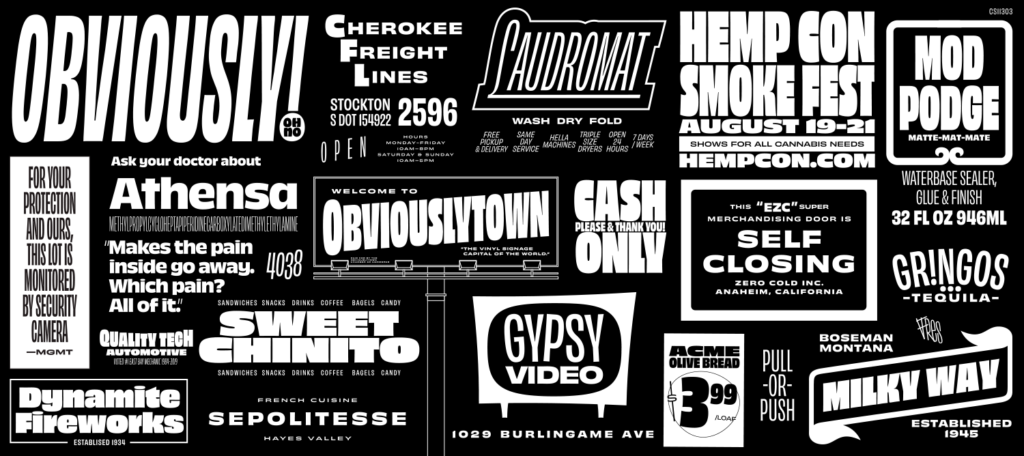
La tecnología variable se lleva de maravilla con las display y Obviously es buena muestra de ello. Una superfamilia compuesta por nada menos que 96 estilos —seis anchos, ocho pesos, tanto en redonda como en itálica—, con todo el sabor de la gran tradición de los rotulistas estadounidenses. «La sutileza es para los pájaros», dice el singular James Edmondson en la descripción, pero la expresividad de Obviously está llena de sutilezas —como todos sus excelentes trabajos— que aumentan exponencialmente gracias al movimiento.
Seguimos con Edmondson, quien en alguna ocasión ha confesado que comienza diseñando en tamaños de visualización y que de ahí pueden surgir tamaños más pequeños, adecuados para texto. Esto explica que Swear sea como una exploración de las posibilidades expresivas y estilísticas del estilo romano
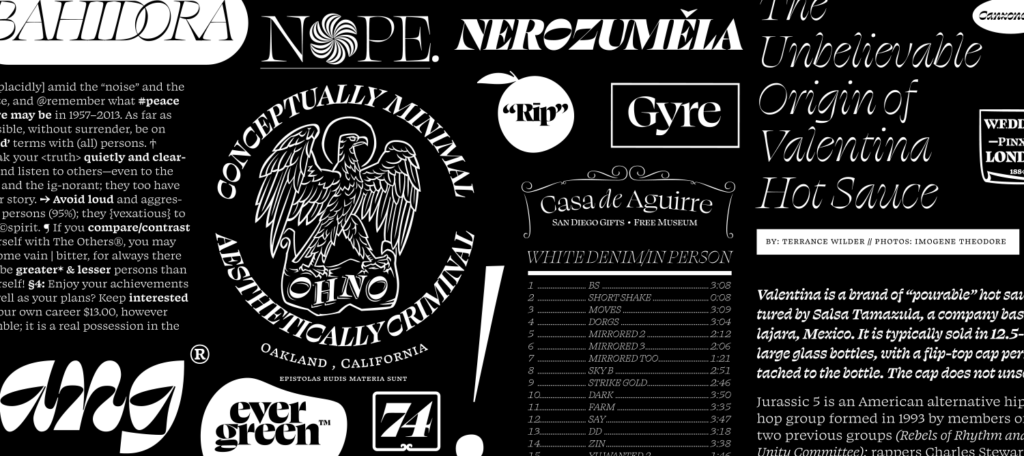
A lo largo de sus tres estilos — text, banner y display— juega con los contrastes, los remates, las curvas e incluso con ligaduras dentro de un mismo carácter, como en el caso de la W. No hay duda de que Edmondson se ha divertido diseñándola, algo que queda patente en la frescura y brillantez de Swear Display.
Termina, de Fort Foundry
Con sede en la ciudad estadounidense de Athens, en el estado de Georgia, localidad natal de los gloriosos R.E.M., Fort Foundry se describen a sí mismos como una fundición que se divierte diseñando tipografías funcionales. Y de manera más pronunciada que sus compatriotas de OHNO TYPE, su catálogo rezuma rotulismo americano.
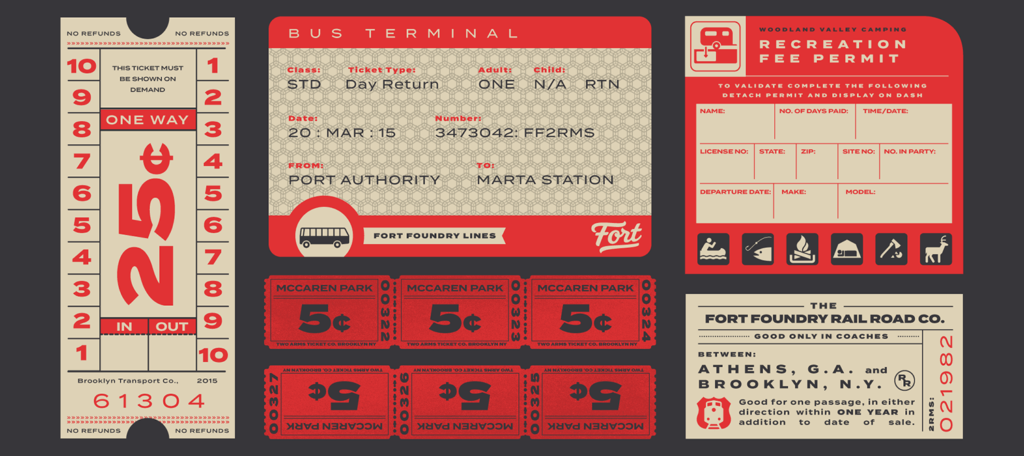
Un buen ejemplo de ello es Termina, que juega con el espíritu de las geométricas y la generosidad de las proporciones de las display. Una considerable altura de x y una majestuosa anchura le confieren nitidez y legibilidad y por tanto la convierten en una tipografía polivalente, con excelentes resultados, por supuesto, en tamaños grandes, pero también en textos de una cierta extensión.
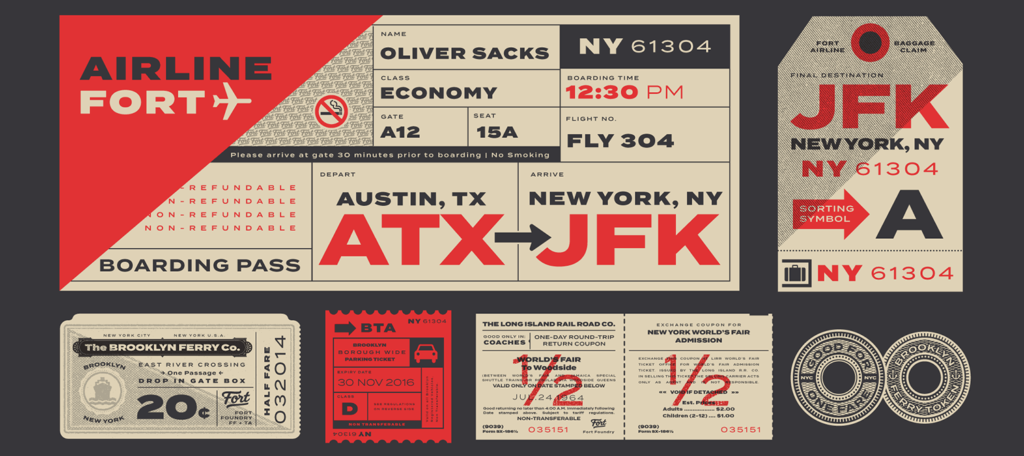
Ella y Sisters de Laura Meseguer
Ella es muchas cosas. Según la propia Meseguer, se trata de una síntesis entre el estilo stencil y la caligrafía. Pero Ella presenta cuatro estilos bien diferenciados, aunque todos ellos bajo esta misma premisa. Romano, uncial, rústico —unas evoluciones de la escritura romana que convivieron durante la misma época—, además de un cuarto llamado brutalista, conviven armoniosamente en este brillante artefacto tipográfico.
Ella es ganadora del TDC 2023 y obtuvo un Certificado de Excelencia Tipográfica
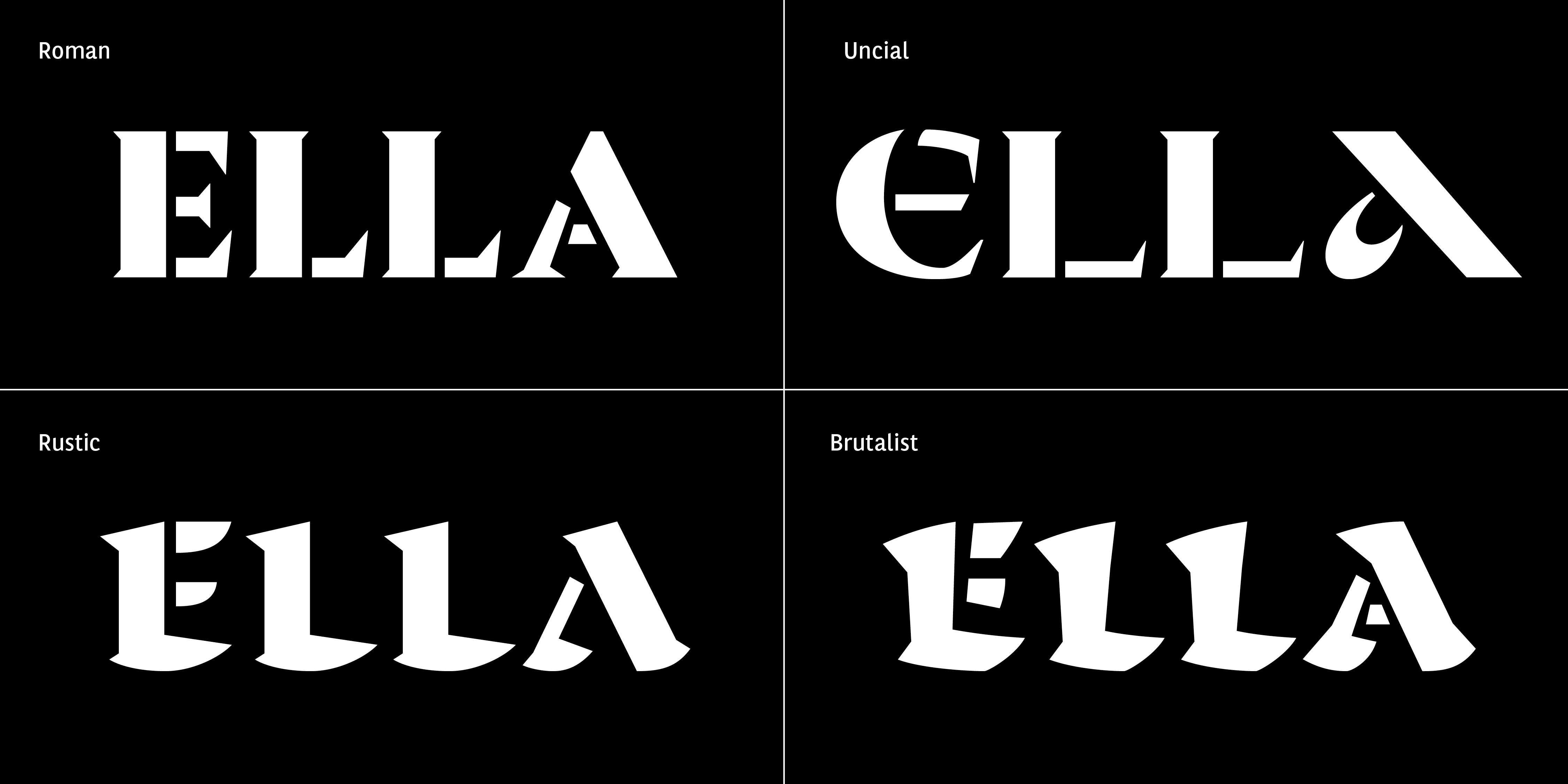
De nuevo Meseguer indaga en las posibilidades del estilo stencil. Caracteres deconstruidos, cuyas partes se hermanan —de ahí el nombre— y se complementan entre sí, «celebrando sus diferencias». Las modulaciones de contraste y demás características formales dan lugar a cuatro estilos, distintos pero hermanados. Sisters se presenta sólo en mayúsculas, lo que reafirma su carácter puramente display.
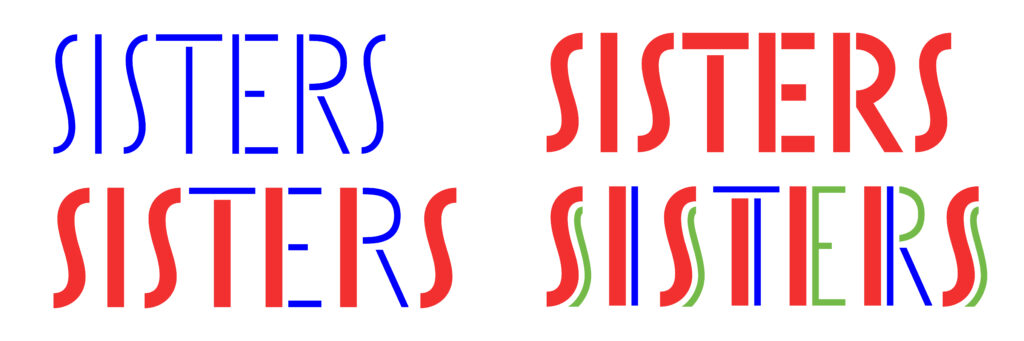
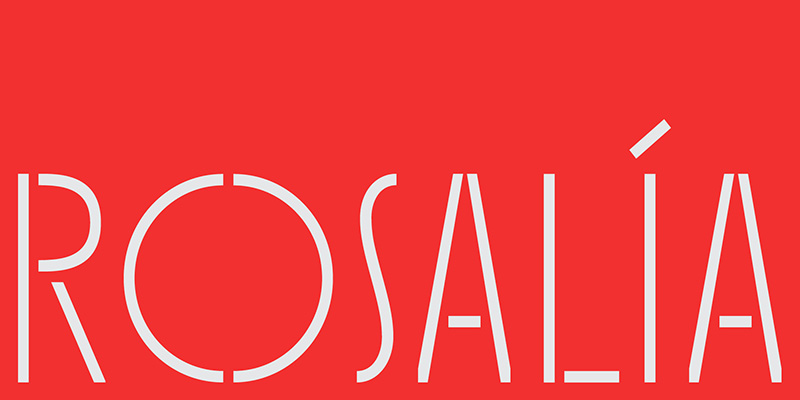
Inge, de Fer Cozzi
Inge Lehmann (1888-1993) nació en Østerbro, Dinamarca y vivió 105 años. Fue una sismóloga pionera en la investigación de los terremotos y descubridora de que la Tierra tiene un núcleo interno sólido dentro de un núcleo externo fundido. Es lo que se conoce, en su honor, como discontinuidad de Lehmann.
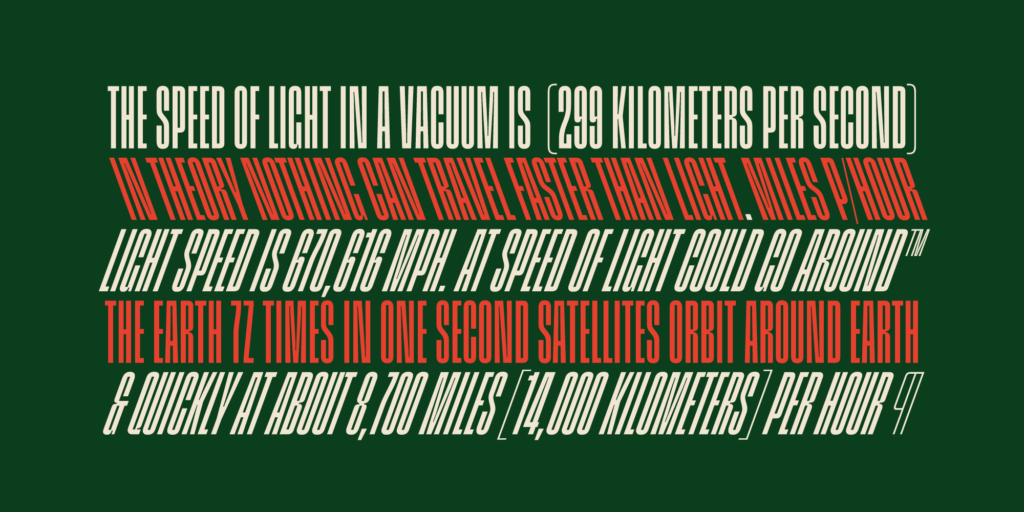
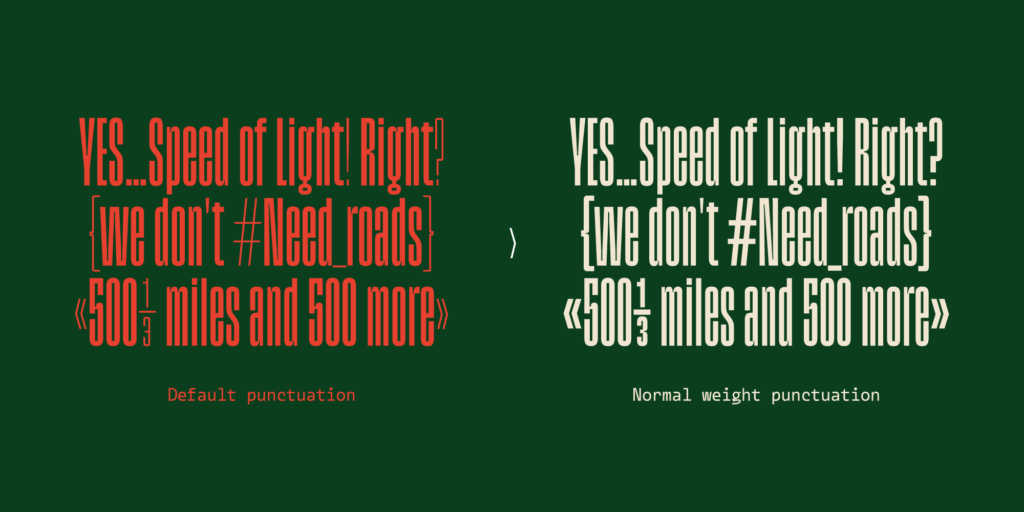
La diseñadora tipográfica argentina Fer Cozzi ha bautizado a esta rítmica y robusta display con el nombre de esta extraordinaria mujer. Inge es condensada y esbelta , por lo que resulta totalmente adecuada para grandes tamaños. Pero su característica principal es su movimiento de lado a lado, pudiendo inclinarse a izquierda y derecha, lo que le puede imprimir velocidad y expresividad, además de una fuerte personalidad.
New Kansas y New Spirit, de Newlyn
Si existe una tipografía capaz de representar la cultura pop del siglo XX en un sentido amplio es Cooper Black, presente en discos de multitud de estilo, títulos de películas y un sinnúmero de marcas de toda clase. No hay duda de que, a pesar de su marcada personalidad y de haber cumplido ya los 100 años, Cooper Black se ha convertido en un icono universal, plenamente vigente a día de hoy.
New Kansas es una adaptación contemporánea y ampliación de este hit, como homenaje y con la intención de darle una nueva vida acorde con las exigencias técnicas y estéticas de la era digital. Aunque originalmente concebida para tamaños grandes, también ofrece un óptimo resultado en textos de una cierta extensión.
Esta New Spirit pretende remarcar la organicidad y espíritu artístico del modelo original. Pero sobre todo, este nuevo diseño, en palabras de Newlyn, supone una exploración de las características más distintivas de Windsor, porque a la hora de rediseñar un clásico de la tipografía el desafío se encuentra en decidir qué mantener y qué cambiar.